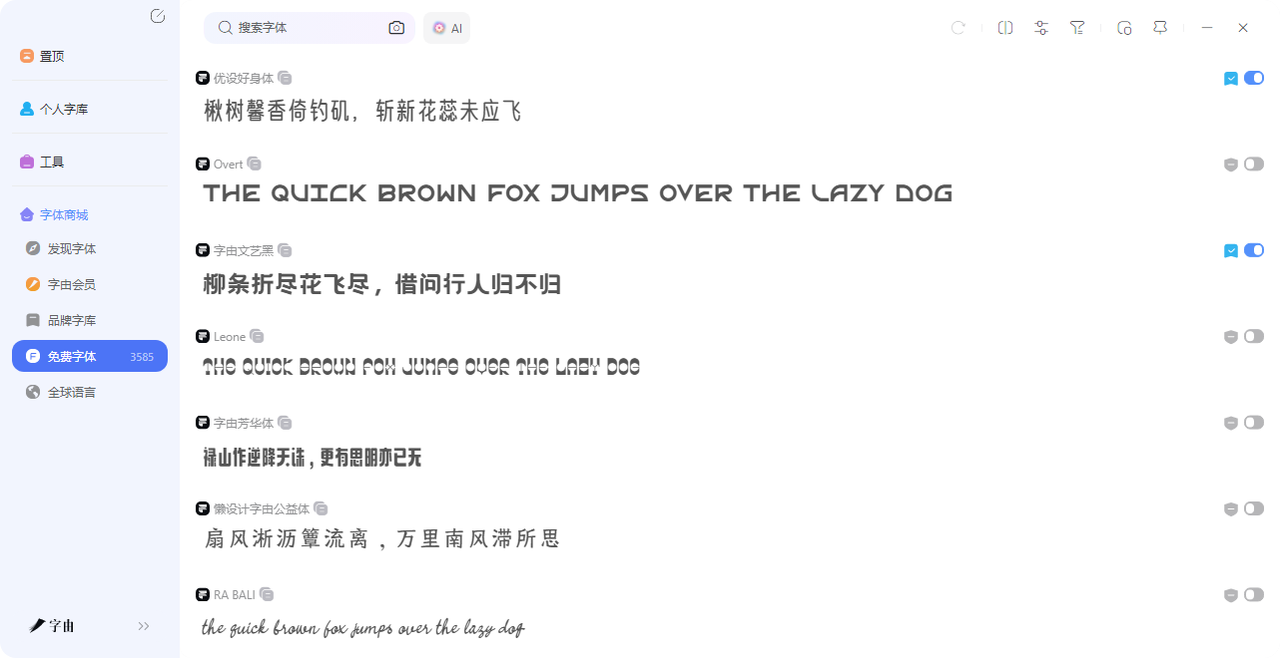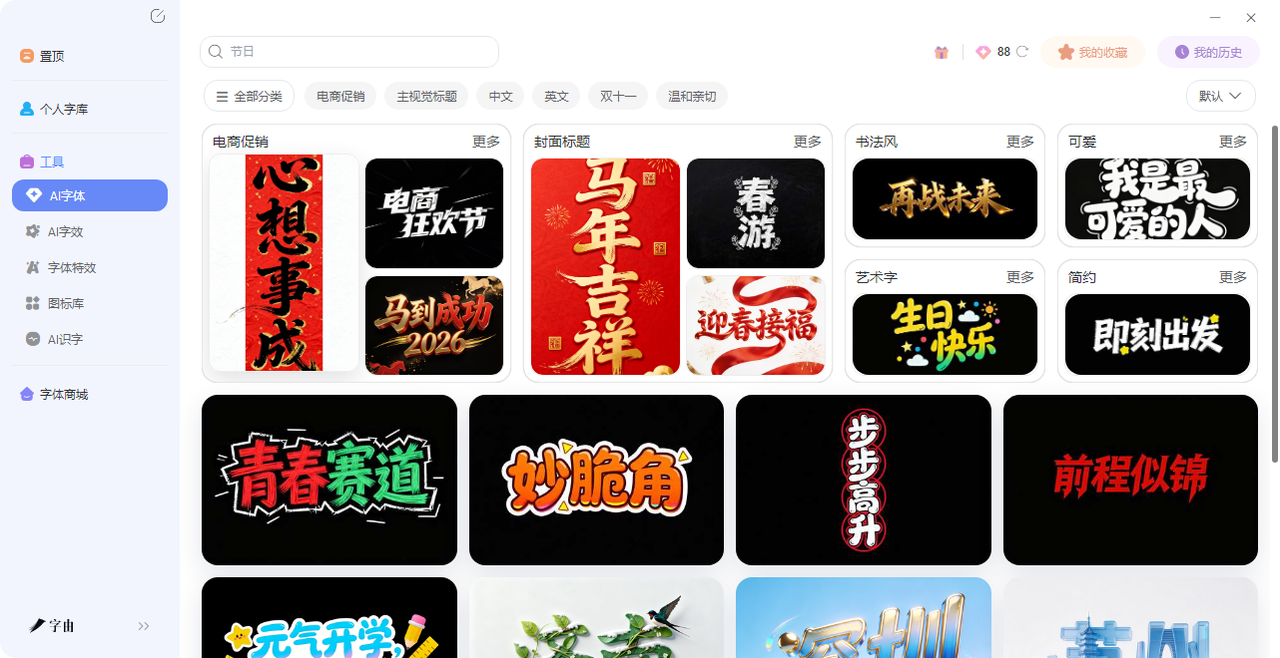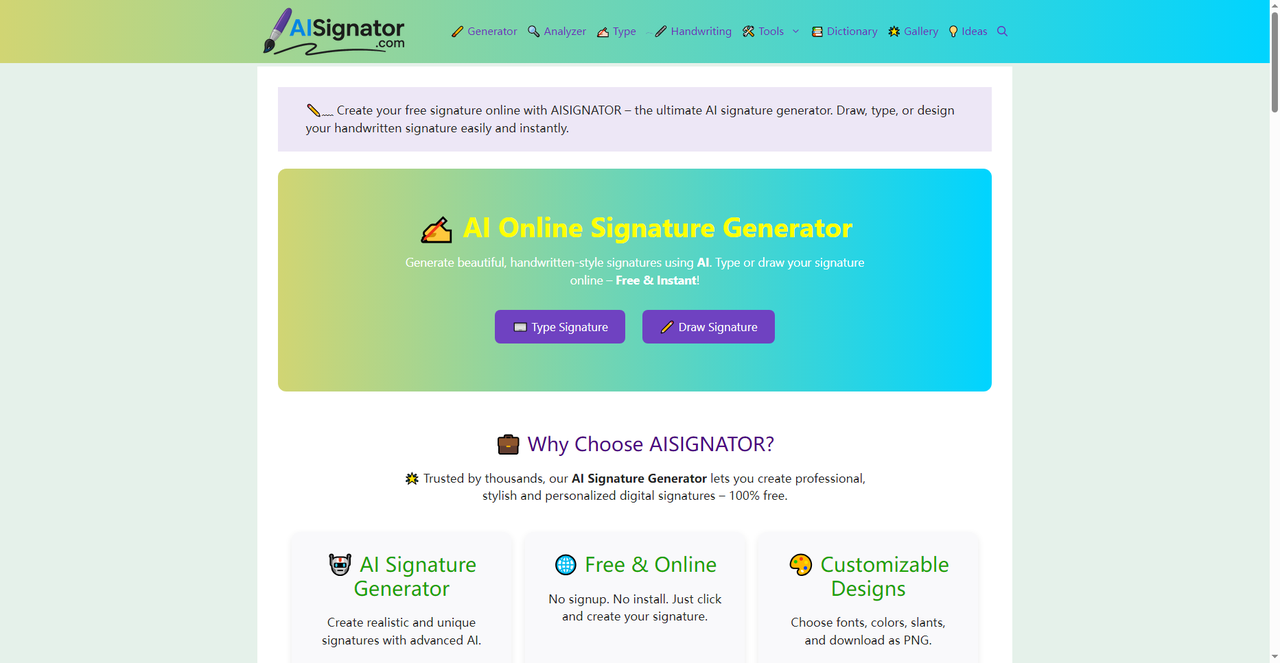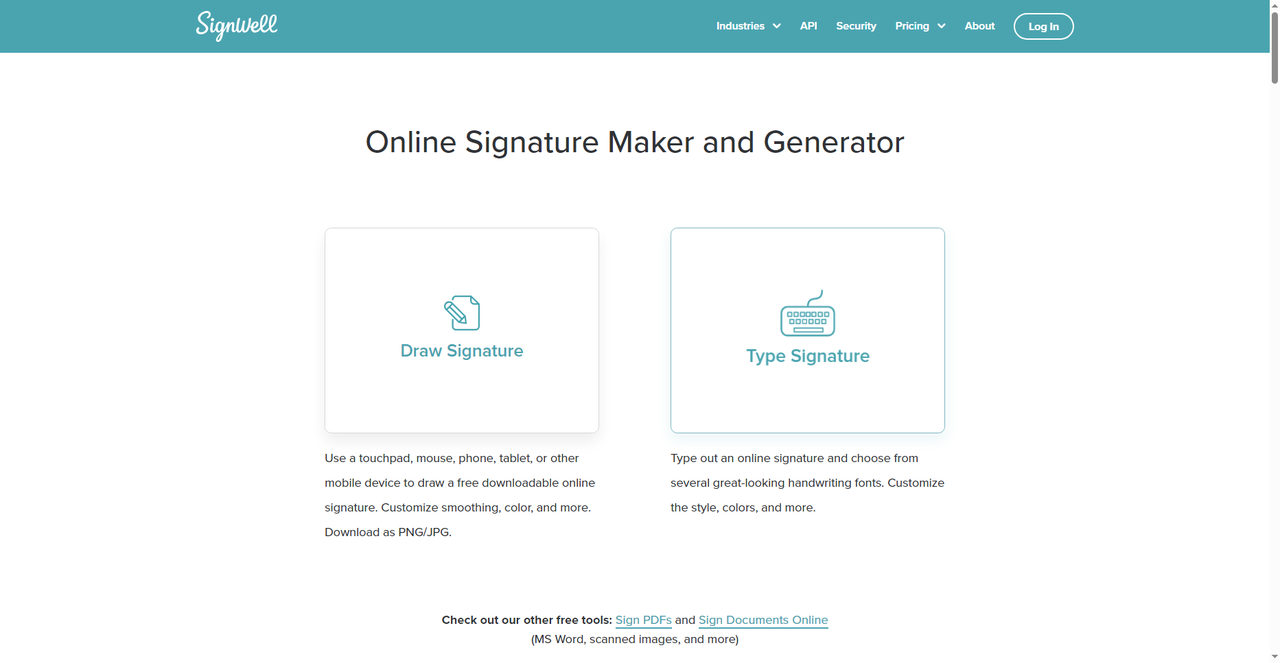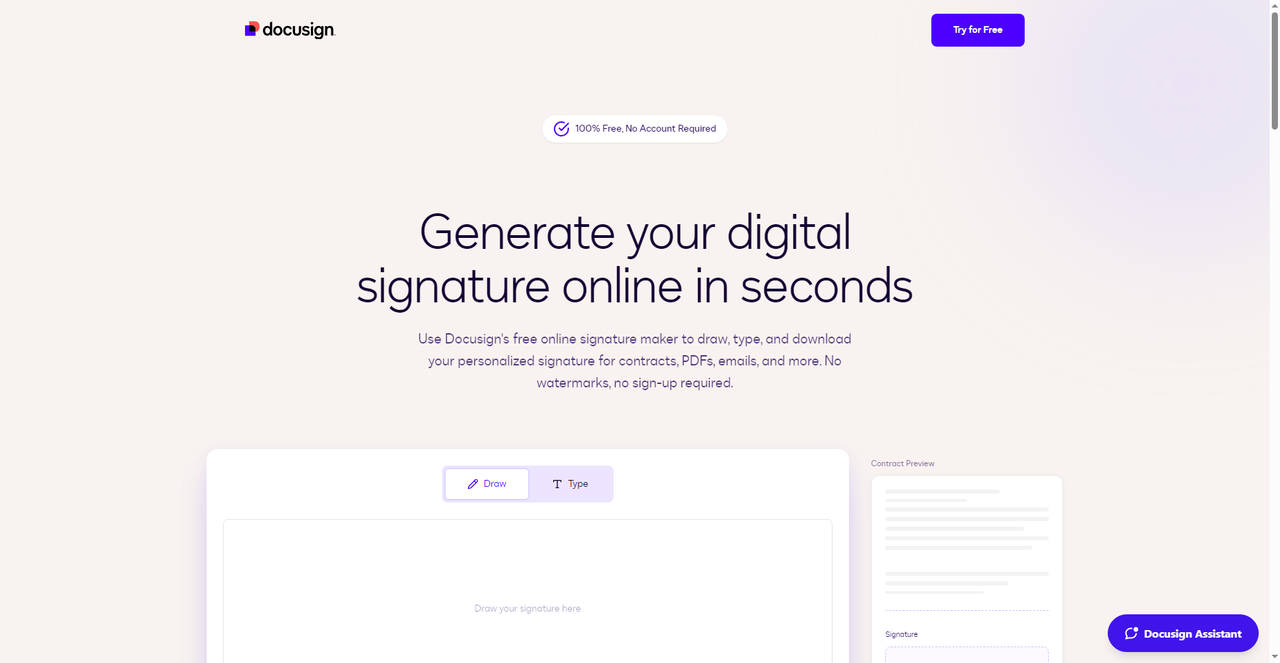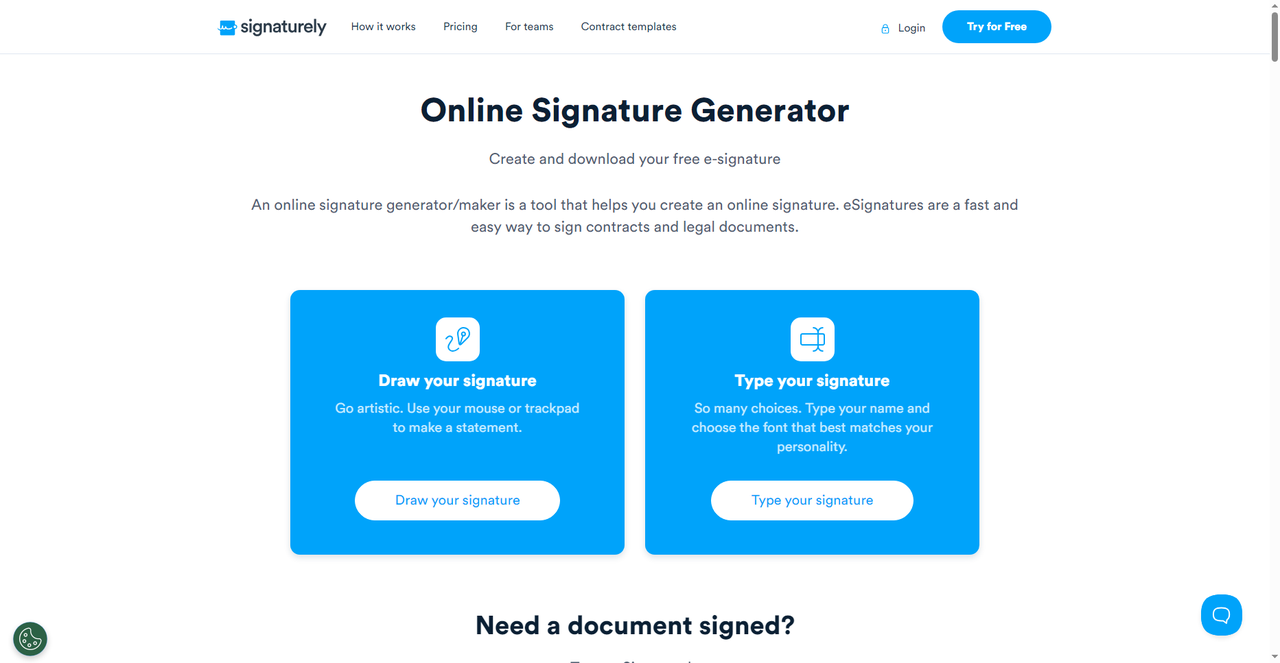
不用找设计师!在线艺术签名在线生成,3秒出效果
想要让自己的签名与众不同但是又担心自己自己不够美观从而写不好?说实话,手写签名这件事,其实不需要专门去练字或者是花钱去找设计师。现在网上有不少在线艺术签名生成工具,输入名字就能出效果,还能下载成图片直接用在电子文档里。今天我就把自己试过的 5 个工具整理出来,看看哪个适合你。
第一个要介绍的在线艺术签名网站是字由,但是很多人可能第一反应是去找专门的签名生成器,其实你手机或电脑里可能已经有了一个很好用的工具——字由(hellofont.cn)。字由是国内一个集字体发现、管理、应用于一体的综合性字体平台,注册用户超过1800万。大家知道字由通常是因为它那上万款字体资源,但其实字由搞定签名设计,至少有三种方法,我现在可以都告诉你。
1. 第一种:从字体库里直接挑
签名说白了就是“字”,而字由最不缺的就是好字体。平台收录了超过10500款精选字体,其中包含大量适合签名的书法体、手写体、艺术体。比如“江西拙楷”带着朴拙的手工感,“字由芳华体”笔画柔和适合文艺风,“字由文艺黑”既有黑体的稳重又带手写感。
你可以在字由的所有字体你慢慢找,找到喜欢的风格,然后在PS、AI等设计软件里用这个字体打出你的名字,稍作调整就能变成专属签名。这是最省事的方式——不用自己一笔一笔画,选个字体就能用。
1. 第二种:AI字体生成签名
字由的AI字体功能,是很多人忽略的一个功能。打开字由客户端,找到工具下的AI字体,里面有一堆字体模板,按书法风、手写风、艺术字等分类排好了。找到喜欢的模板,点击“做同款”,输入你的名字,再点“立即生成”,等30秒左右就能得到设计好的签名文字。
1. 第三种:云字库存好常用签名字体
如果你已经找到几款适合做签名的字体,但又不想每次重新找,字由的个人云字库功能就能派上用场。把你用过的、喜欢的字体收藏起来,以后想换风格了直接来云字库找就行。只要账号还在,收藏的字体就不会丢。
2、AI Signator
第二个网站叫AI Signator。从名字就能看出来,这是一个专门用AI技术做签名生成的工具。它的核心逻辑很简单:输入你的名字,AI自动分析并生成多种风格的签名方案。这个工具的使用方式很灵活——你可以选择直接打字输入名字,让AI根据你输入的文本生成签名;也可以用手绘板或鼠标在画布上亲手画出签名,系统会把你的笔迹转化为数字格式。生成后可以调整字体风格、颜色、倾斜角度等参数,最后下载成PNG格式的图片。
AI Signator主打的就是“专业”两个字。如果你需要的是一个看起来有设计感、能用在正式场合的签名,这个工具生成的效果会比普通字体直接打出来的名字精致不少。而且它是免费的,不需要注册账号,打开网页就能用。
3、Signwell
第三个网站叫Signwell。和前面两个做签名生成的工具不太一样,Signwell的核心定位其实是电子签名平台,用来处理合同、协议这类需要法律效力的文件签署。但它也内置了一个很方便的签名生成器。在Signwell的签名生成功能里,你可以用鼠标或触控板手绘签名,也可以直接打字输入名字,系统会提供几种不同的字体风格让你挑选。生成好的签名可以直接用在Signwell平台上的文档里,不需要单独下载再导入。
4、DocuSign
第四个网站是DocuSign,这个我想重点介绍一下,它在法律效力和安全性方面做得相当到位,DocuSign的强项其实不只是“生成一个好看的签名图”,而是它背后那套完整的电子签名体系。用DocuSign签的文件在很多国家和地区都具有法律效力,适合用来签署正式合同、租赁协议、工作offer等。如果你需要一个既有设计感又有法律保障的在线艺术签名方案,DocuSign 值得你选择。
5、Online Signature Generator
最后一个要介绍的网站是一个通用的Online Signature Generator,这类工具在市面上有很多,功能大同小异,主打的就是简单直接。打开这个工具后,你有两种方式创建签名:一种是“Draw Signature”,用鼠标或触控板在画布上直接手绘签名,支持调整平滑度、颜色等参数;另一种是“Type Signature”,输入你的名字,从系统提供的几种字体里选一个喜欢的,自动生成签名效果。生成后可以下载成PNG或JPG格式,用在各种需要签名的电子文档上。
这类通用签名生成器最大的优势就是“轻”。不需要注册账号,不需要安装任何软件,打开网页就能用。如果你只是偶尔需要生成一个签名图片,不想折腾太多设置,这种工具最省事。